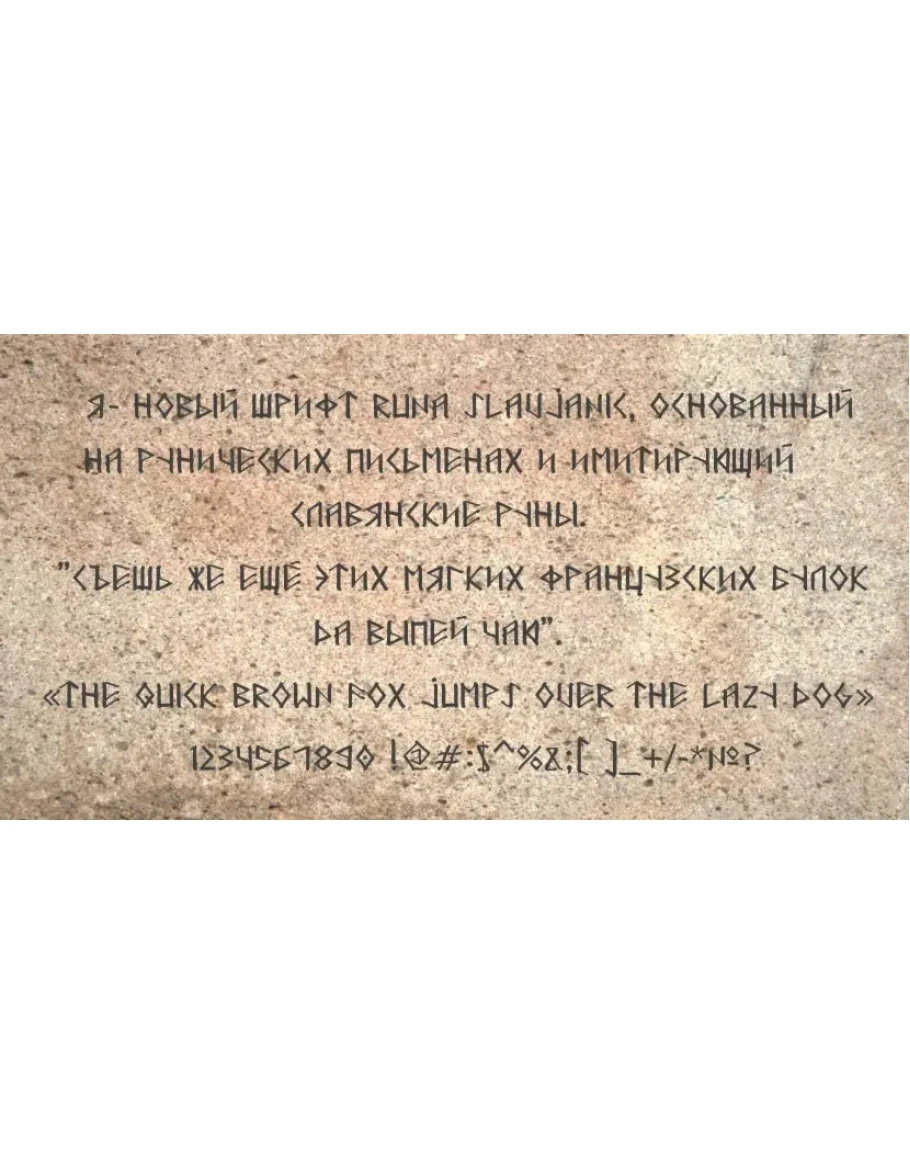
Рунический шрифт Runa Slavjanic
Рунический шрифт на основе славянских рун.
Язык: русский, английский.
Цифры: есть.
Доп. символы: все символы клавиатуры.
Рунический шрифт Runa Slavjanic